漫威新电影《毒液》来袭,这一波海报设计让你心潮澎湃
漫威新电影《毒液》已上映,作为漫迷的小编自然不拉下,尤其那场飞车之战,看的心潮澎湃。电影过瘾海报也画面感爆棚,毒液那粘腻又充满力量的躯体、湿漉漉的长舌头搭配上那萌萌的性格让人顿觉可爱呢,先上图:
水墨风
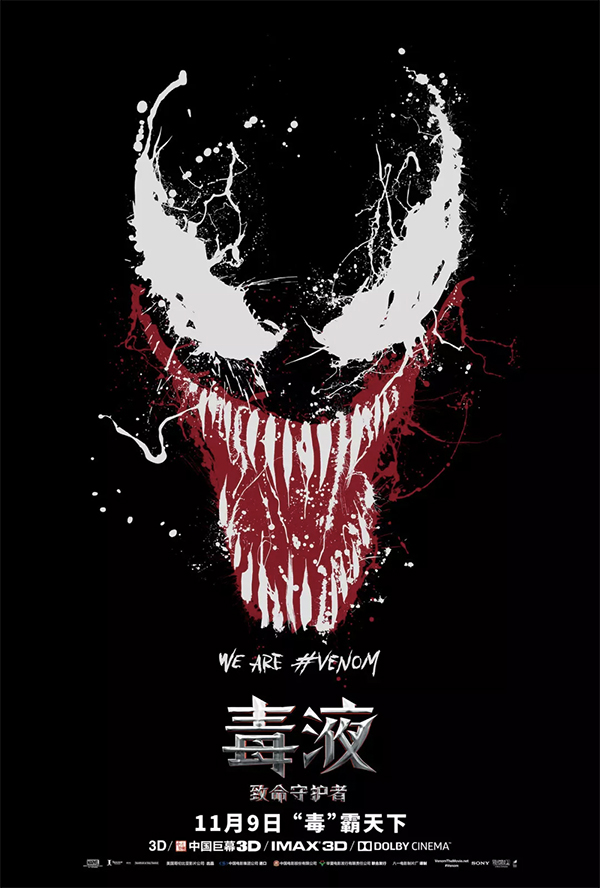
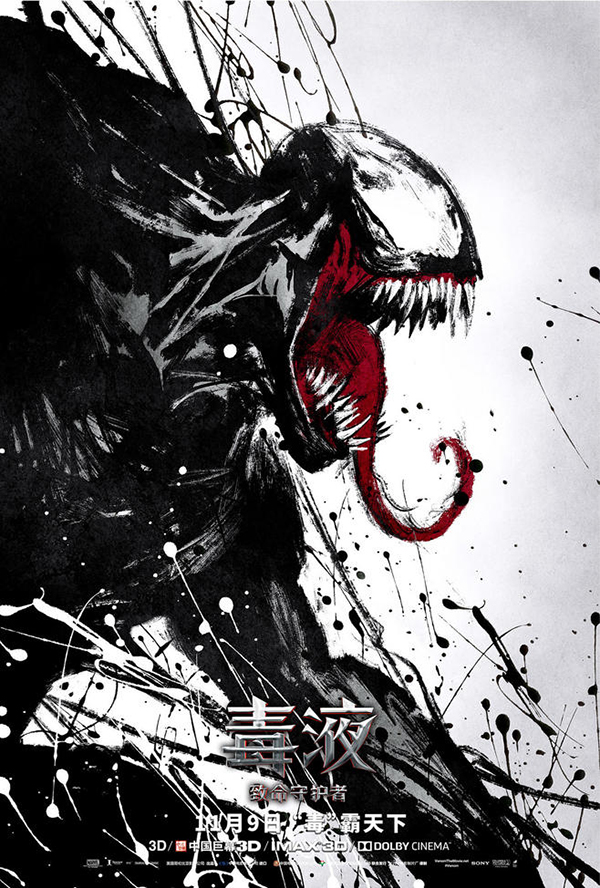
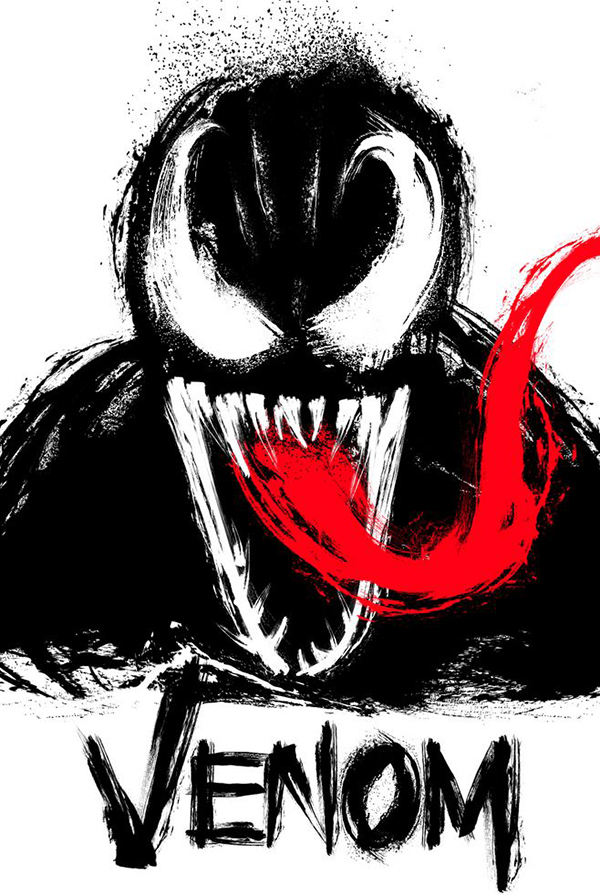
正式版
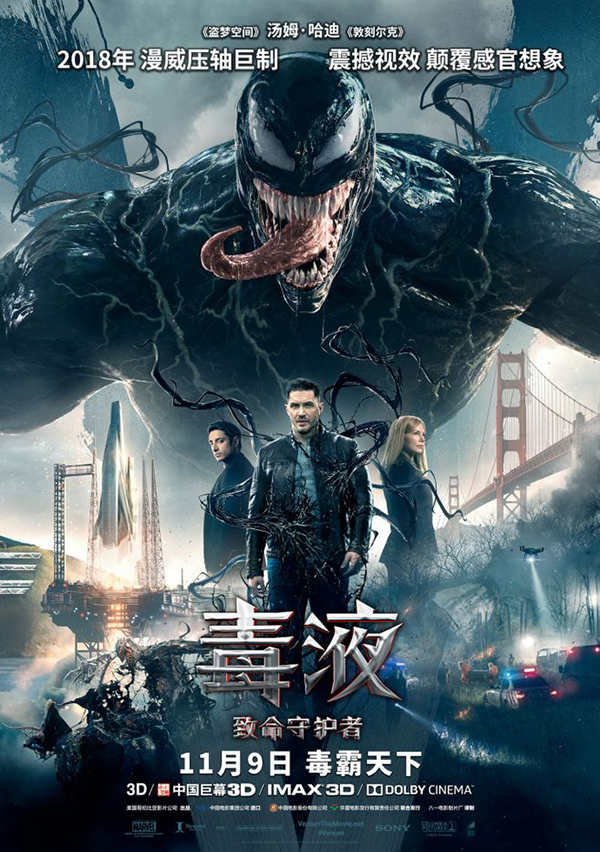
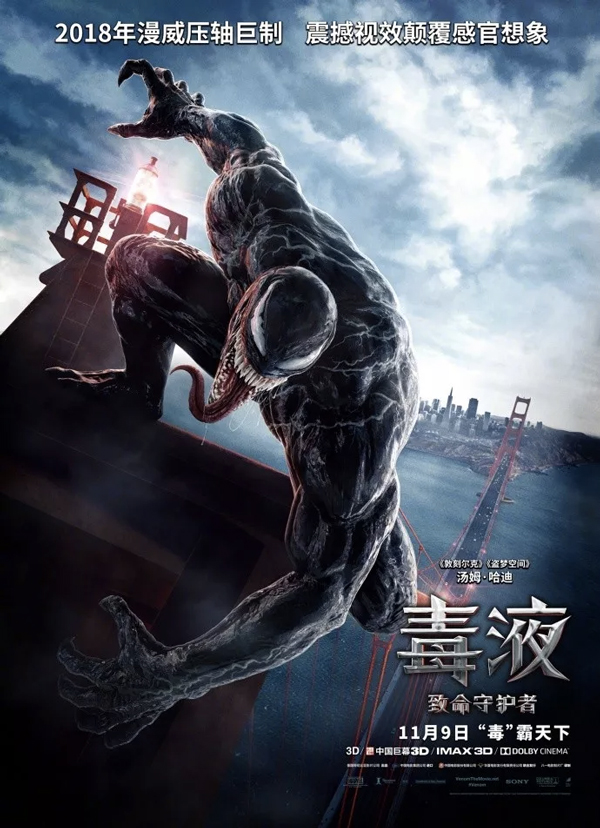
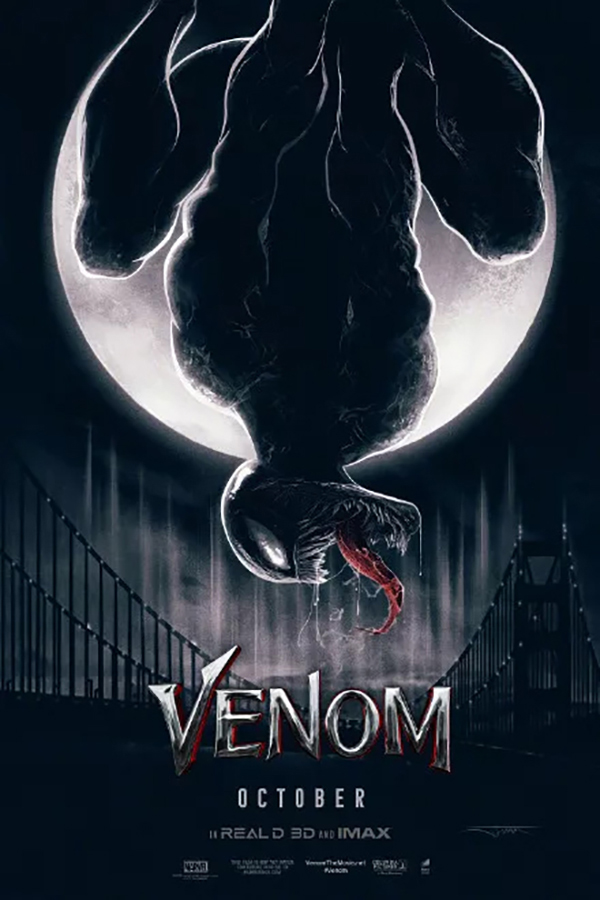
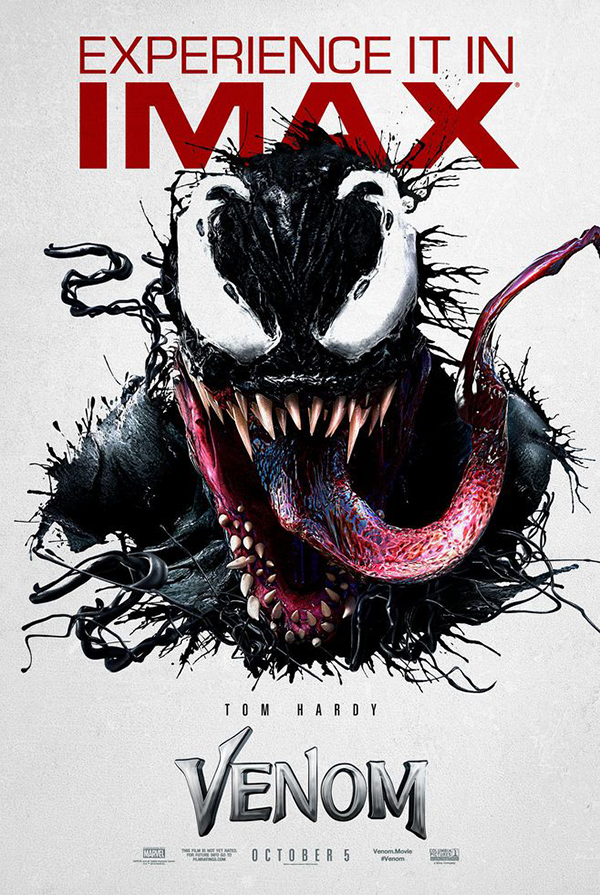
万圣节神秘风
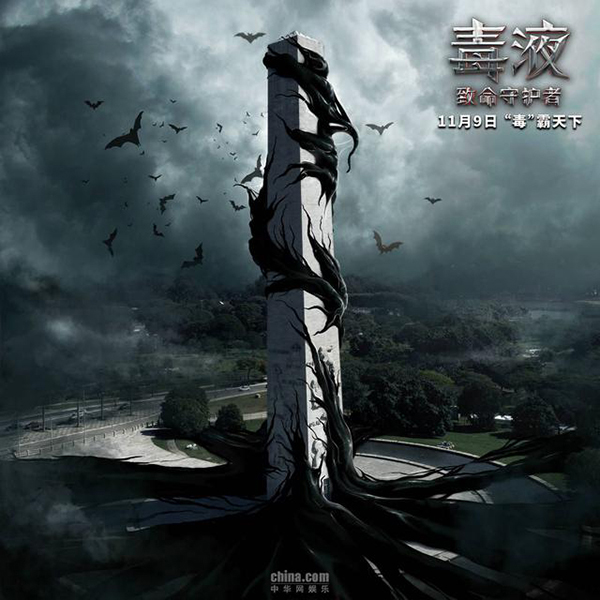
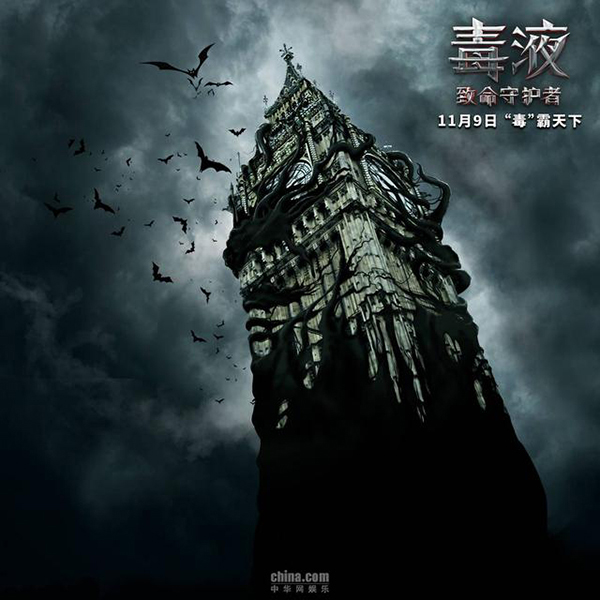
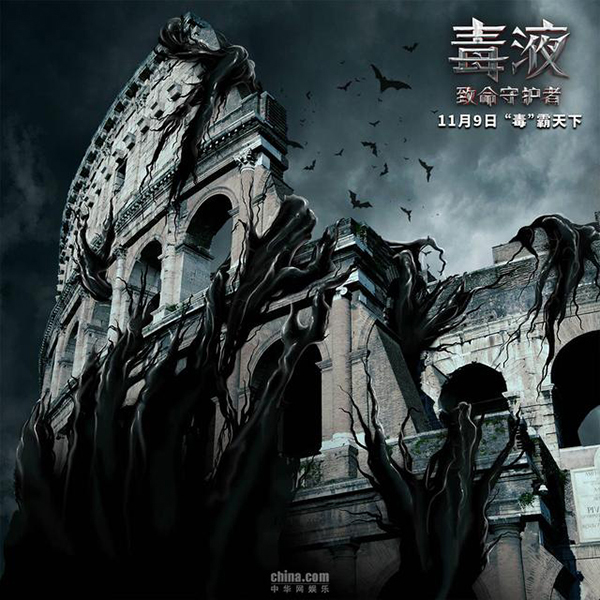
海报中字体小编也帮大家分析好了,类似方正剑体,都是比较尖锐有力的字体。